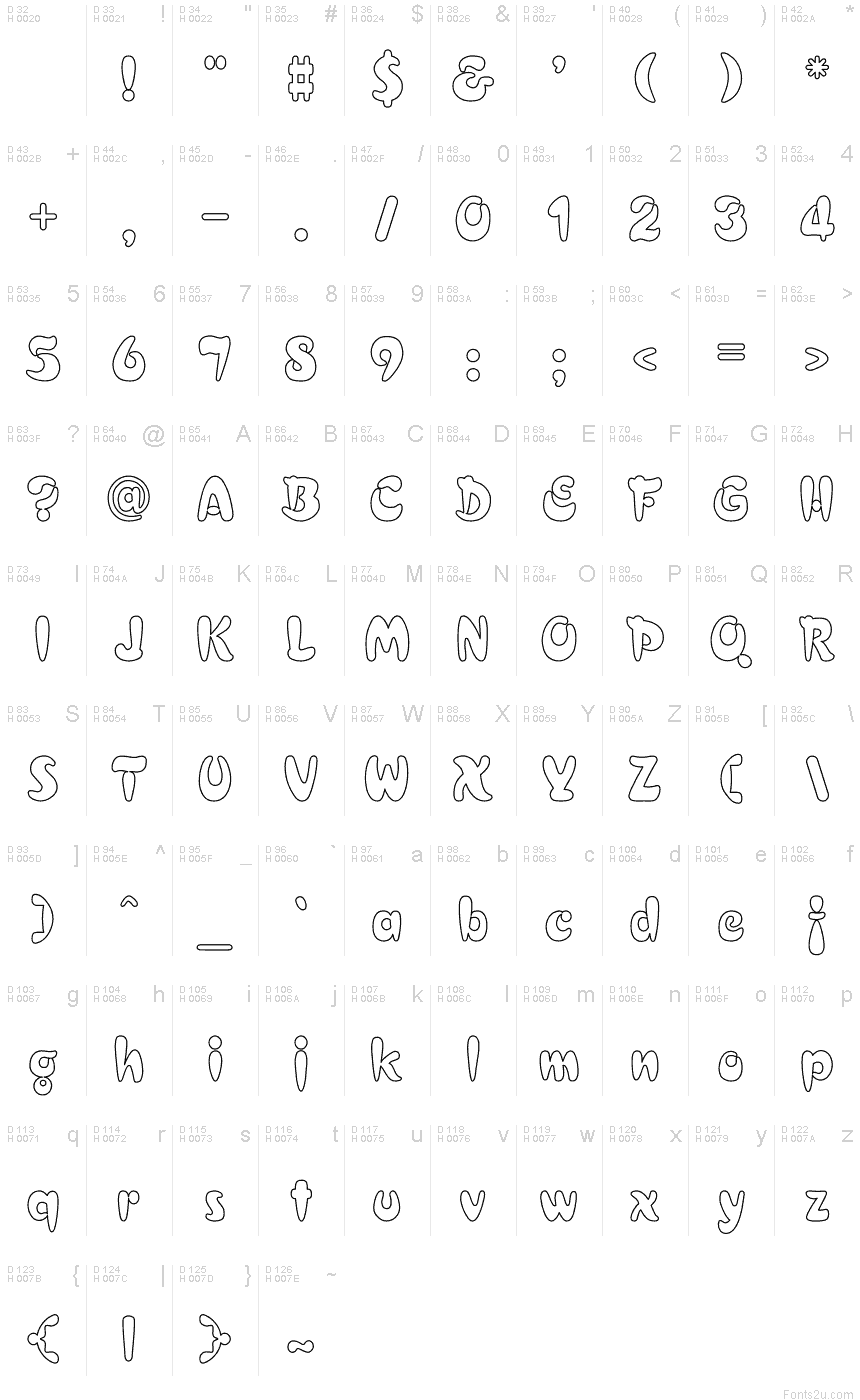
Electrik Hollow è un font display in stile fumetto gratuito, caratterizzato da lettere che sembrano gonfie d'aria e tracciate con un contorno nitido, quasi a inchiostro. Gli spazi vuoti donano a ogni parola un aspetto leggero e vivace, come se fosse pronta per essere colorata o accesa come un'insegna al neon. Le curve arrotondate, la spaziatura generosa e le proporzioni giocose la rendono immediatamente leggibile anche in dimensioni grandi.
Usa Electrik Hollow per dare un tocco di energia divertente a poster per bambini, inviti di compleanno, packaging di caramelle o giocattoli, effetti sonori in stile fumetto, grafiche per i social media e design di adesivi. Questo font gratuito dà il meglio di sé se usato in grande e in grassetto; abbinalo a un carattere sans serif geometrico semplice per il testo di accompagnamento.
Electrik Hollow